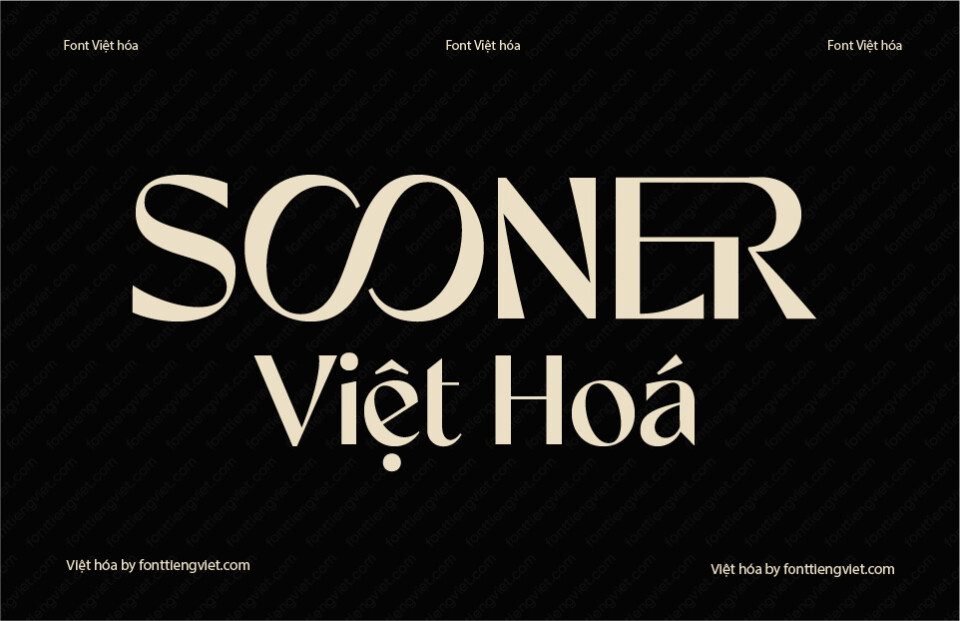
Font Việt hóa 1FTV VIP Sooner
Giới thiệu về bộ Font Việt hóa 1FTV VIP Sooner
Trong thế giới đồ họa hiện đại, việc tìm kiếm một bộ Font Miễn Phí chất lượng cao và phù hợp với tiếng Việt luôn là ưu tiên hàng đầu của các nhà sáng tạo. Font Việt hóa 1FTV VIP Sooner nổi lên như một giải pháp hoàn hảo dành cho những ai yêu thích sự kết hợp giữa phong cách cổ điển và hơi thở đương đại. Đây là bộ phông chữ được tinh chỉnh kỹ lưỡng về dấu câu, đảm bảo không xảy ra lỗi hiển thị khi soạn thảo các văn bản tiếng Việt phức tạp. Với đường nét thanh mảnh nhưng vẫn giữ được độ chắc chắn, bộ phông này giúp mọi bản thiết kế trở nên chuyên nghiệp và lôi cuốn hơn bao giờ hết. Đặc biệt, đối với các bạn học sinh và giáo viên, công cụ này hỗ trợ đắc lực trong việc trình bày bài giảng hoặc làm báo cáo một cách sinh động.
Đặc điểm nổi bật của Font Việt hóa 1FTV VIP Sooner
Phong cách thiết kế tinh tế và hiện đại
Điểm mạnh nhất của Font Việt hóa 1FTV VIP Sooner chính là sự đa dạng trong ứng dụng. Phông chữ sở hữu cấu trúc chữ cái cân đối, khoảng cách giữa các ký tự được tính toán khoa học giúp người đọc không bị mỏi mắt. Các nét chữ mang tính nghệ thuật cao, phù hợp cho cả tiêu đề lớn lẫn các đoạn nội dung dài. Sự tinh tế này giúp người dùng dễ dàng truyền tải thông điệp một cách rõ ràng nhất. Dù bạn đang thiết kế một tấm thiệp chúc mừng, một bìa sách giáo khoa hay một poster sự kiện trường học, bộ phông này đều đáp ứng tốt các tiêu chuẩn thẩm mỹ khắt khe nhất hiện nay.
Khả năng tương thích và tối ưu hóa tiếng Việt
Ứng dụng thực tế của Font Việt hóa 1FTV VIP Sooner trong đời sống
Sáng tạo nội dung giáo dục và truyền thông
Trong môi trường học đường, Font Việt hóa 1FTV VIP Sooner là trợ thủ đắc lực để làm mới các slide thuyết trình. Thay vì sử dụng những phông chữ mặc định nhàm chán, việc thay đổi sang bộ font này sẽ giúp bài giảng thu hút sự chú ý của học sinh hơn. Ngoài ra, các câu lạc bộ trường học có thể dùng phông chữ này để thiết kế áo lớp, băng rôn hoặc các tờ rơi thông báo. Sự trẻ trung và thanh lịch của bộ chữ sẽ tạo nên dấu ấn riêng biệt cho các hoạt động tập thể. Bạn cũng có thể áp dụng phông chữ này vào việc làm thiệp handmade hoặc viết nhật ký số để tăng thêm phần cá tính và sáng tạo cho sản phẩm của mình.
Kết luận về bộ Font Việt hóa 1FTV VIP Sooner
Tổng kết lại, Font Việt hóa 1FTV VIP Sooner là một lựa chọn không thể bỏ qua cho kho tài nguyên thiết kế của bạn. Với sự kết hợp giữa vẻ đẹp thẩm mỹ và tính ứng dụng cao, bộ font này chắc chắn sẽ làm hài lòng cả những người dùng khó tính nhất. Hãy nhanh tay cập nhật bộ chữ này vào bộ sưu tập của mình để biến những ý tưởng trên trang giấy thành những tác phẩm nghệ thuật thực thụ. Để tìm kiếm thêm nhiều bộ sưu tập ấn tượng khác, bạn có thể truy cập ngay trang web Font Miễn Phí, Font Việt Hóa, Font Việt hóa 1FTV VIP Sooner và trải nghiệm thế giới đồ họa đa sắc màu. Chúc bạn có những giây phút sáng tạo thật tuyệt vời và thành công với những dự án sắp tới của mình.